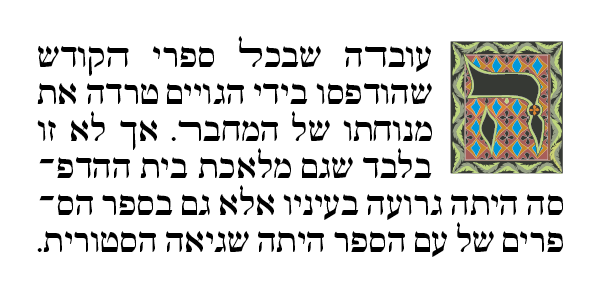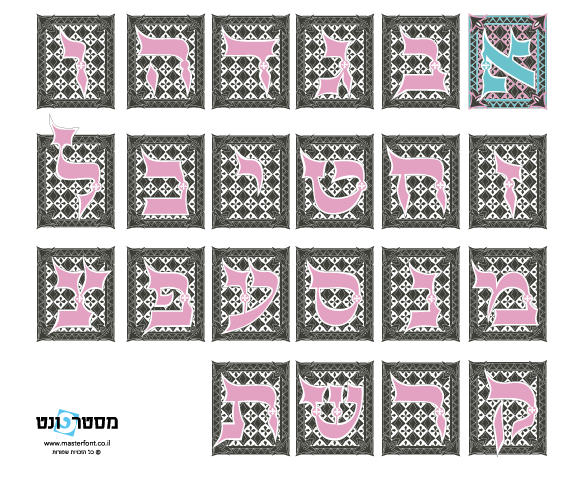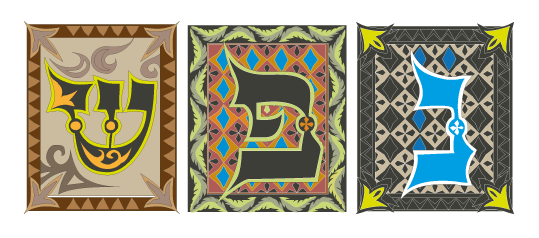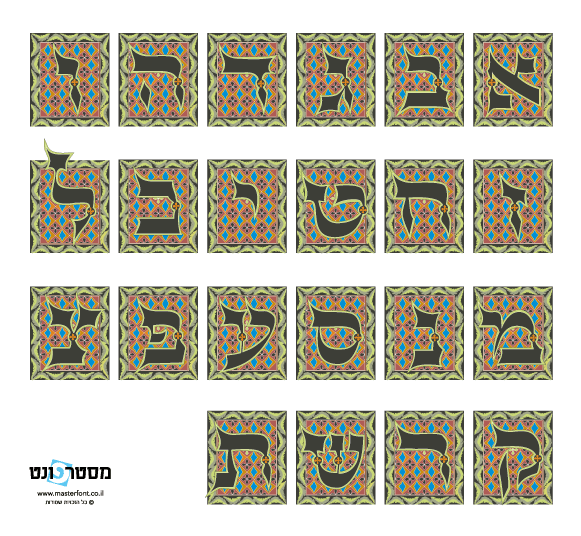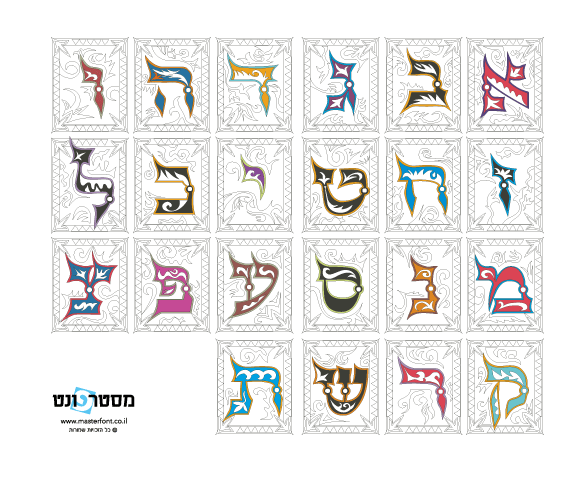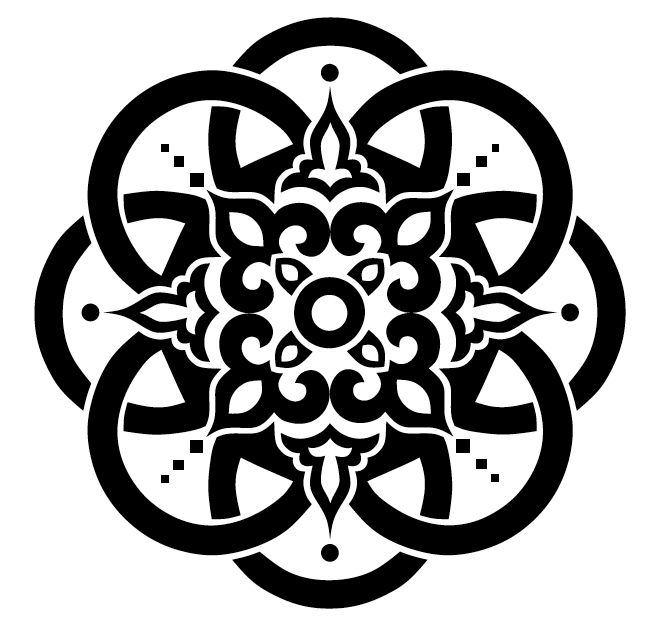
אורנמנטים
אוסף
מרהיב ויוצא דופן של אורנמנטים (עיטורים)
ומסגרות מוכנים לעבודת עיצוב בכל נושא.
האוסף
מכיל 186
אלמנטים
גרפיים ועוצב בכדי לתת מגוון רחב של
סגנונות שונים למעצבים,
הוצאה
לאור ופרסום.
והנה על קצה המזלג, דוגמאות לאורנמנטים השונים:
פתיח פונט
סידרה של איורים מורכבים של כל אותיות האלפבית העברי. זה אינו פונט כמקובל אלא 3 סדרות של אותיות מאוירות בעלות מאפיינים צורניים וגיאומטריים שונים וכל אחת מעוצבת בסגנון יחודי לה.
עיצוב: נאוה אייבל.